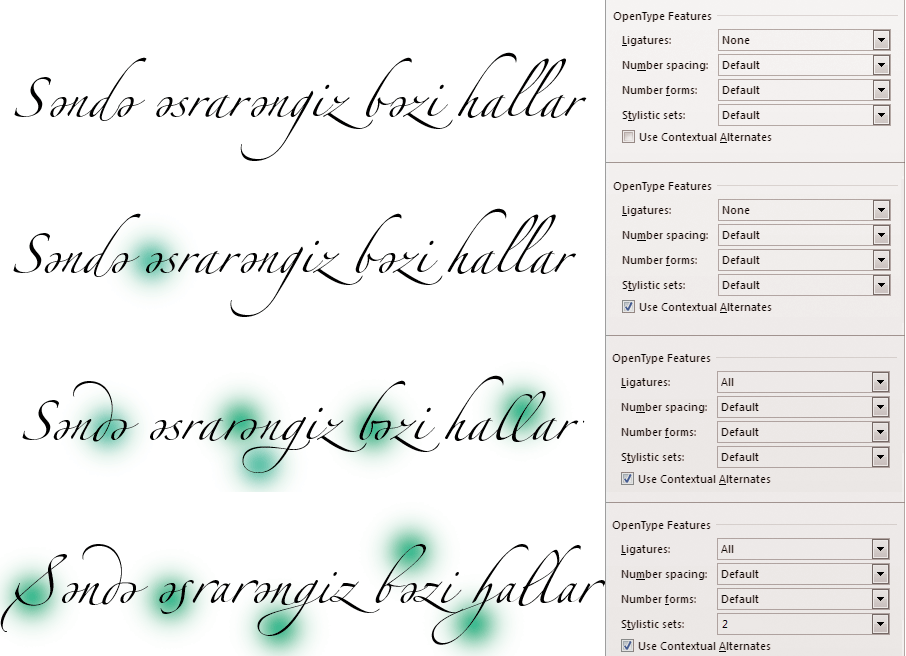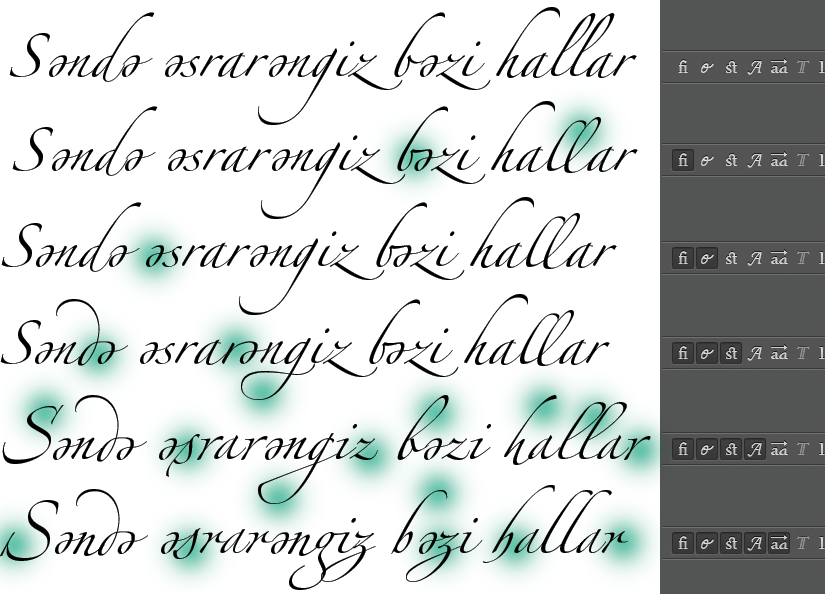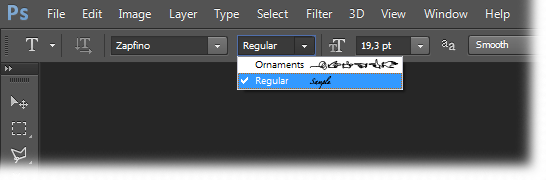
1998-də alman font dizayneri Hermann Zapf özünün 80 illik yubileyi münasibətiylə düzəltdiyi çox məşhur fontdur. Əl yazısı - kaliqrafik stildə olduğundan çox mürəkkəb quruluşu var. Məsələn, diqqət etsəniz, sözün ortasındakı hər hansı bir "ə" hərfi ilə, sözün əvvəlindəki "ə" və eləcədə "də", "fə", "rə" və s. birləşmələrdəki hərflərin stili fərqlidir.
Zapfino da tam bir il əvvəl əlavə etdiyimiz Desire kimi alternativ hərflərə sahibdir. O vaxt da alternativlərin necə istifadə edildiyi videoda izah edilmişdi. Bu dəfə bir az da Word və Photoshop kimi standart programlarda bəzi alternativlər və ligaturaların istifadəsini izah edəcəm.
Word
Mətni seçib Fonts.. dialoq qutusunda Advanced tab bölümündə OpenType Features zövqümüzə uyğun dəyişiklikləri edə bilərik. Fərqi göstərmək üçün aşağıda misal var:
Photoshop
Mətni seçib Character pəncərəsində zövqümüzə uyğun dəyişiklikləri edə bilərik. Fərqi göstərmək üçün aşağıda misal var:
Zapfino fontu ornament əlavələri ilə gəlməkdədir, ətraflı məlumatı bu .pdf faylından tapa bilərsiniz. Photoshopda Ornaments ayrı font kimi deyil, ailə fərdi kimi istifadə edilir: